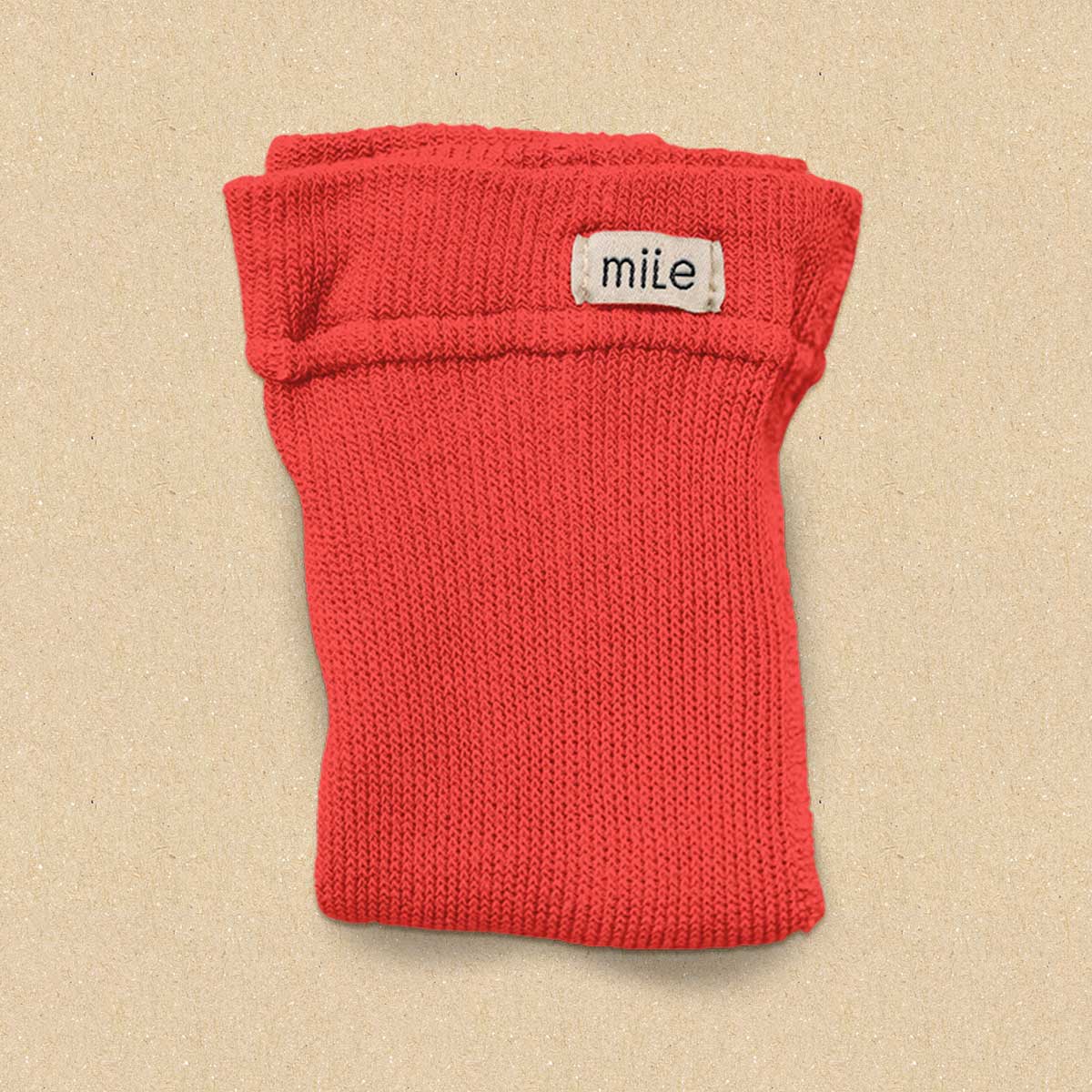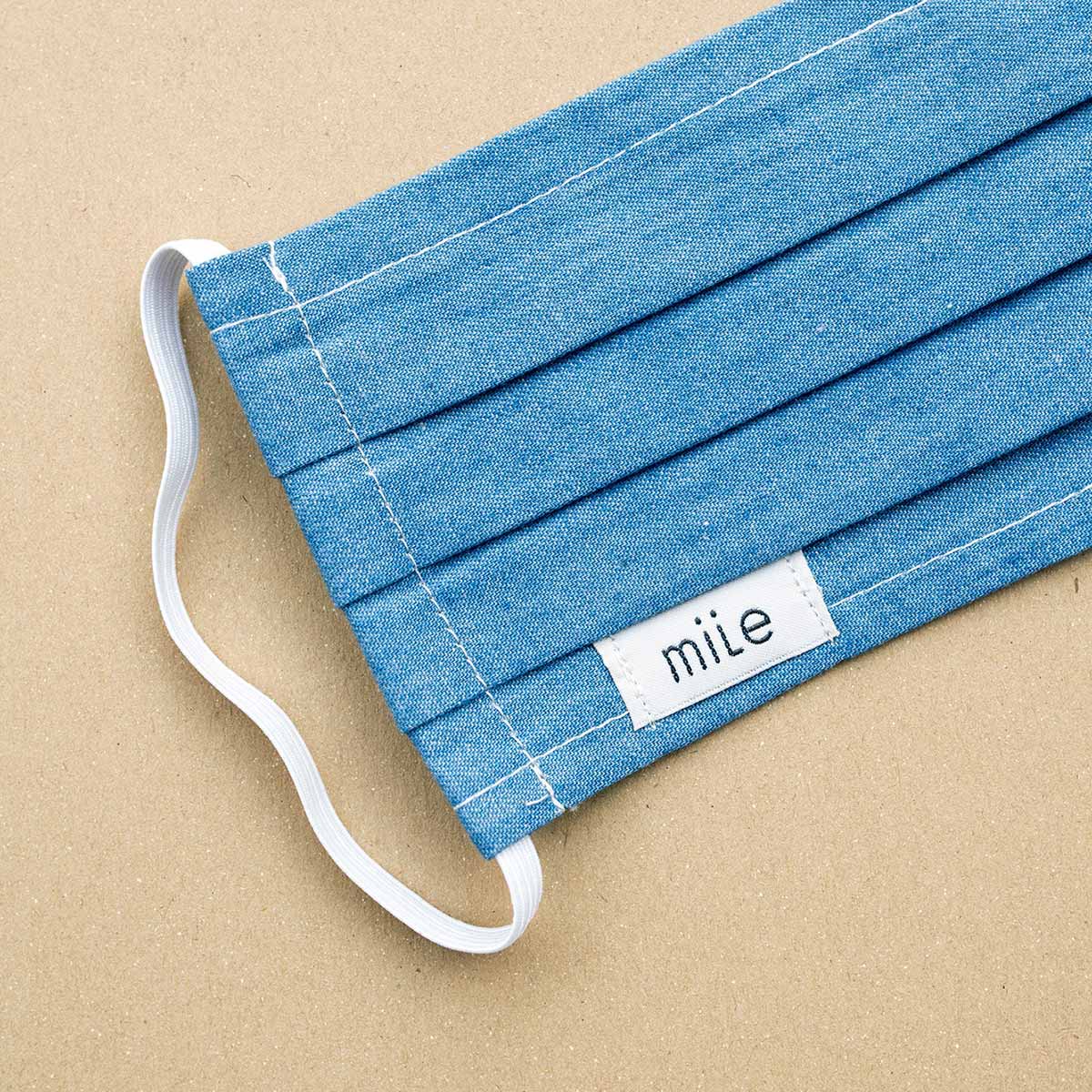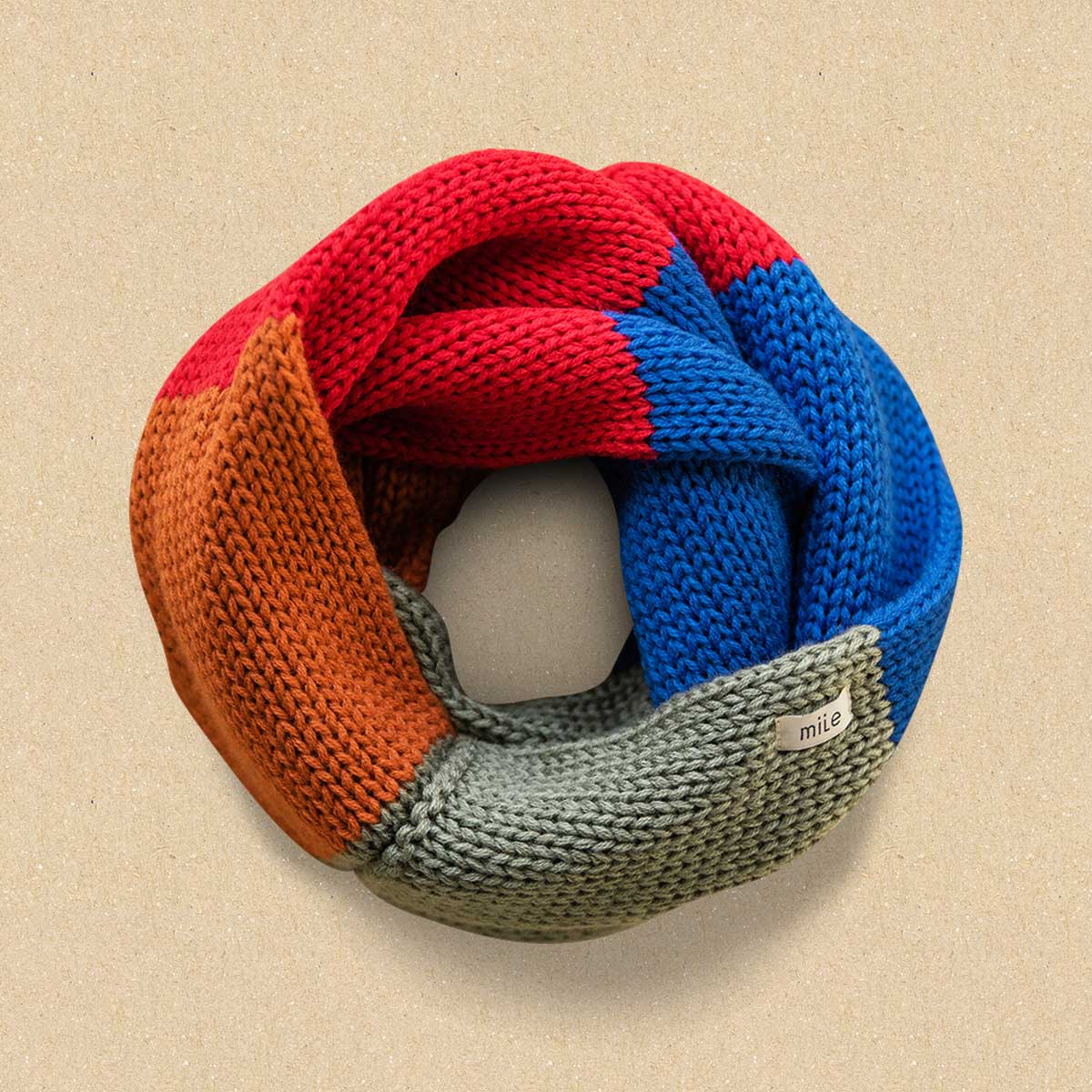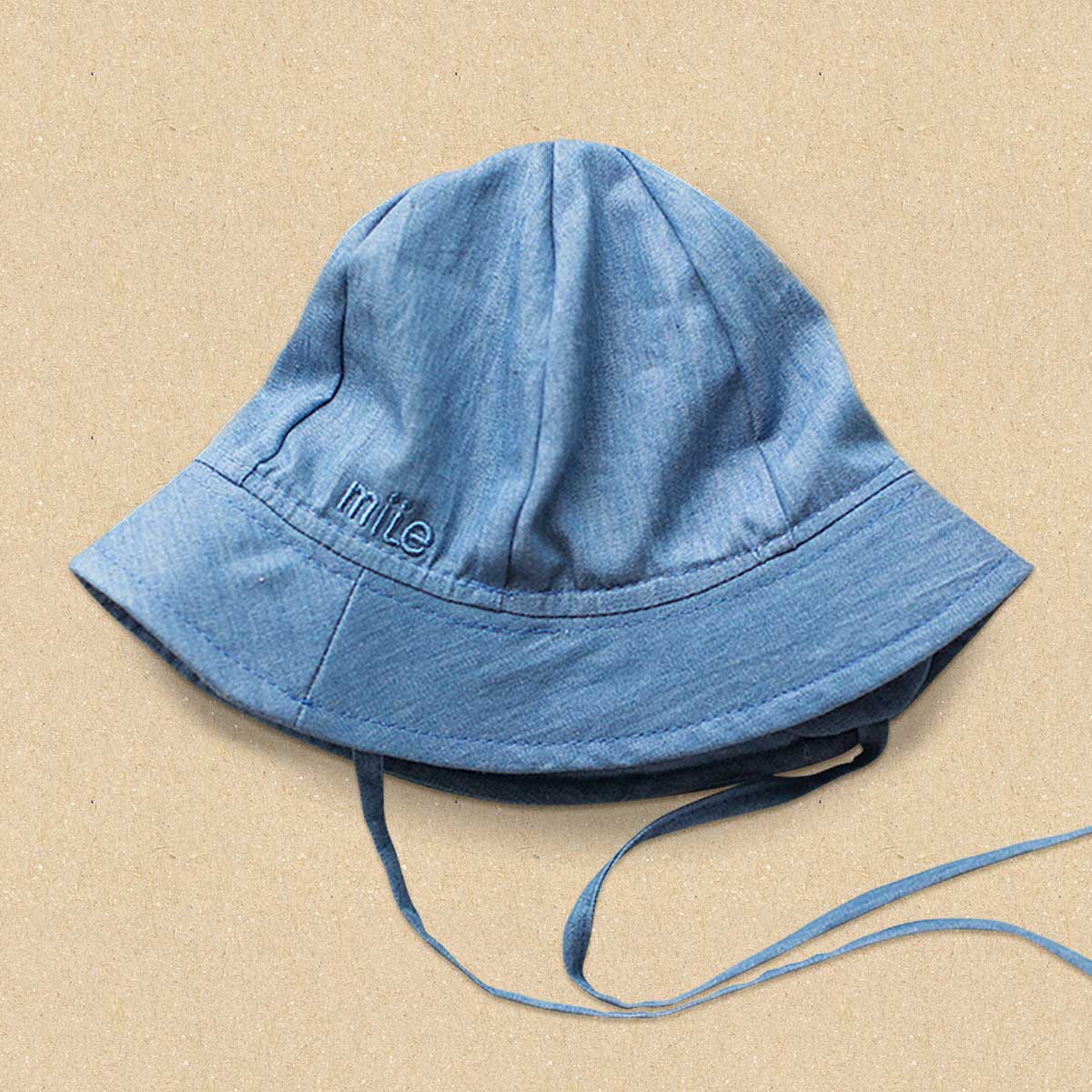
mile
Logo pre slovenskú značku oblečenia pre deti a ich rodičov Mile.
Kondenzované unicase sans-serifové logo so zaobleným ukončením ťahov prostredníctvom bodiek reprezentuje duo zakladateliek značky a dvojica IL je vizuálnou metaforou rodiča kľačiaceho pri dieťati.